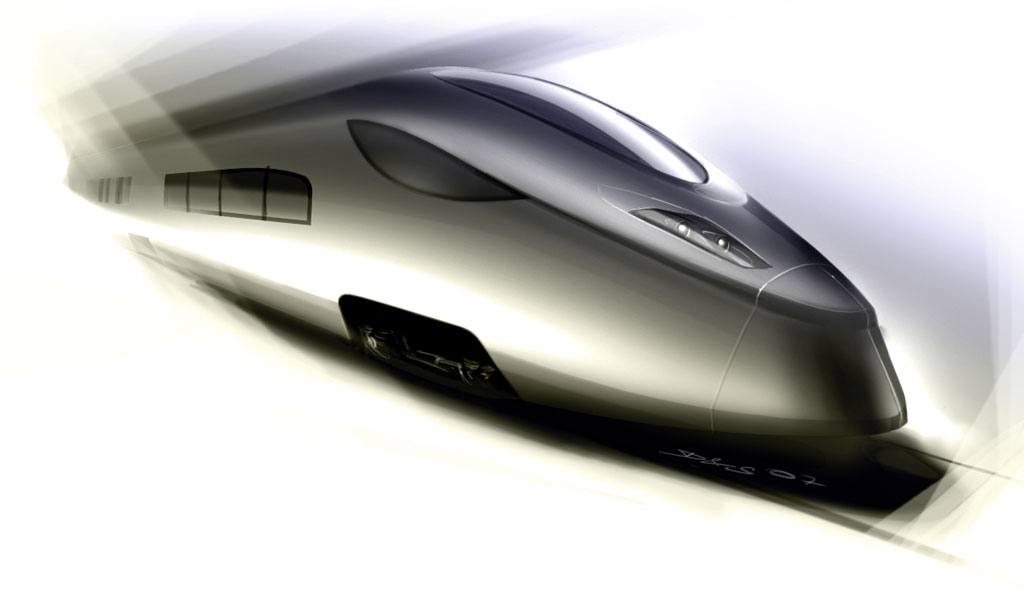
SNCF un logo de plus en plus dyslexique
Nous voici dans la phase ubuesque d’un matériel roulant qui évolue vers un aérodynamisme de plus en plus marqué, laissant le logo en place sur le quai des signifiants démodés. Et pourtant je me souviens des explications du DA de Carré Noir concernant la forme du cartouche qui devait rappeler la forme du matériel roulant. Voilà ce que c’est que de concevoir des logos anecdotiques. Leur obsolescence va plus vite que les entreprises qu’ils sont censés représenter. La SNCF n’est pas la seule entreprise à «produire» une identité proche de l’anecdote. Ça devient la règle de nos jours. Un grand billet d’analyse bientôt sur ce sujet. En attendant je vous laisse découvrir le nouveau AGV d’Alsthom:
L’AGV, que le groupe n’hésite pas à comparer à l’avion géant A380, est conçu pour rouler plus vite que le TGV : 350, voire 360 km/h contre 320 km/h au maximum pour le TGV Est. Autre particularité, l’AGV possède une motorisation répartie sur toutes les voitures du train, plutôt que concentrée sur les deux motrices en tête et en queue, ce qui permet, selon Alstom, de gagner de la place pour les passagers et de réduire les coûts de maintenance. Des moteurs dits « à aimants permanents » permettent aussi de consommer moins d’énergie, fait valoir le groupe français. (Le Monde en date du 5 février 2008)
Je n’aime pas le logo de la SNCF mais le point avancé ici ne me semble pas pertinent dans le cas particulier de la SNCF puisque la société renouvellera son parc de TGV d’ici 2020, ce qui laisse encore de beaux jours à cet horrible logo. De plus – même si la SNCF achètera sans doute l’AGV – il ne faut pas oublier qu’Alsthom n’est pas le seul fournisseur de rames et la SNCF se fournit également chez Siemens et Bombardier (dont les TER ont une forme proche de l’actuel logo SNCF) [Source: JT France2 si je me souviens bien]